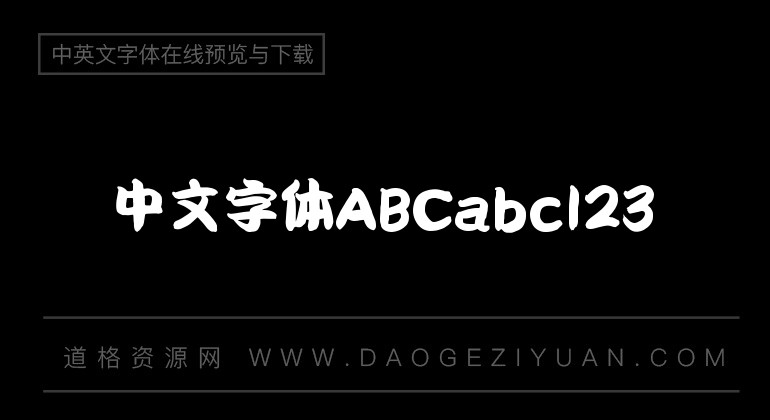
潮字社勘亭流简繁字体是一种中文字体,其名字来源于古代书法家赵孟頫所创的“勘亭流”字体。该字体有简体和繁体两种形式,是一种经典的书法字体,具有很高的艺术价值和实用性。 潮字社勘亭流简繁字体结合了传统书法艺术和现代排版技术,字形流畅自然,线条流畅优美,具有非常好的可读性和美观度。其对于中文排版和印刷非常有用,广泛应用于书籍、广告、标志、展示等设计领域。 潮字社勘亭流简繁字体的特点是线条简洁流畅,笔画粗细适中,字形规整美观,整体感觉清新自然,适合用于各种设计场合。同时,该字体也非常容易阅读,字形与间距都非常舒适,可以提高阅读体验。文件名:ChaoZiSheKanTingLiuJianFan-Shan(REEJI-CHAO-KanTingLiuGBT-Flash)-2.ttf
潮字社勘亭流简繁是一款非常不错的手写艺术字体,具有很好的视觉感,适合于文化类的宣传设计、商业类品牌的广告和产品包装设计以及个性化文字排版等较多场景。